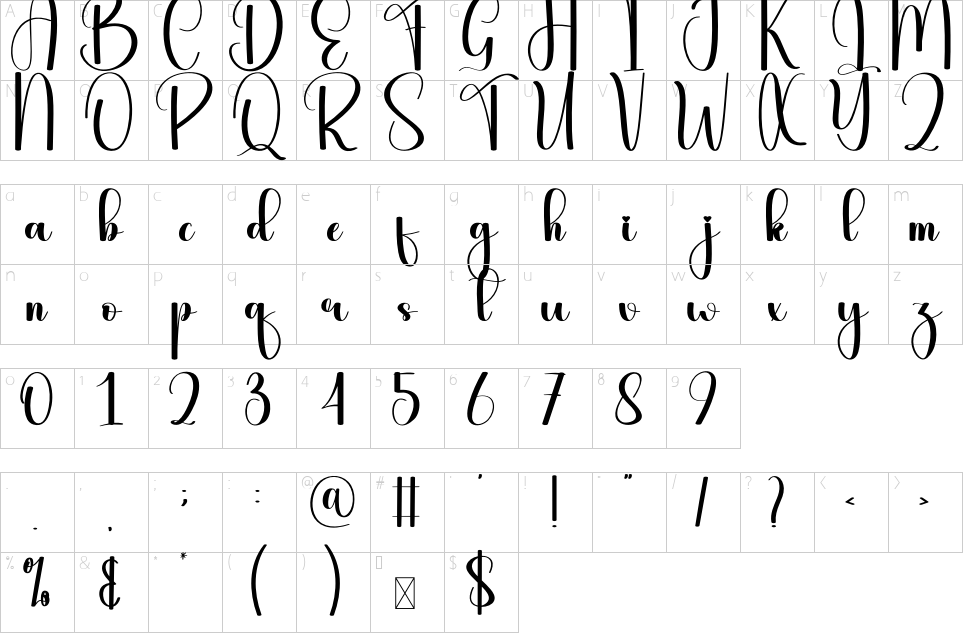
Descubra o charme delicado e elegante da Angelica font, uma fonte gráfica livre e simples, ideal para projetos digitais que buscam uma sensação agradável e contemporânea. Arquitetada por William Jhordy, a Angelica se destaca por seu design suave e agradável ao olhar, que se torna perfeitamente acessível tanto para desktops quanto para dispositivos móveis. Seu design minimalista e arquitetado com cuidado cria uma atmosfera acolhedora e versátil, perfeito para uma variedade de usos. Com seu design cuidadosamente criado, a Angelica se destaca como uma escolha inteligente para projetos gráficos, desde textos simples até designs mais elaborados. A fonte já foi baixada 425 vezes, demonstrando seu valor e aprimorando a experiência de uso para muitos designers. Descubra por si mesmo a beleza discreta e versátil da Angelica font.